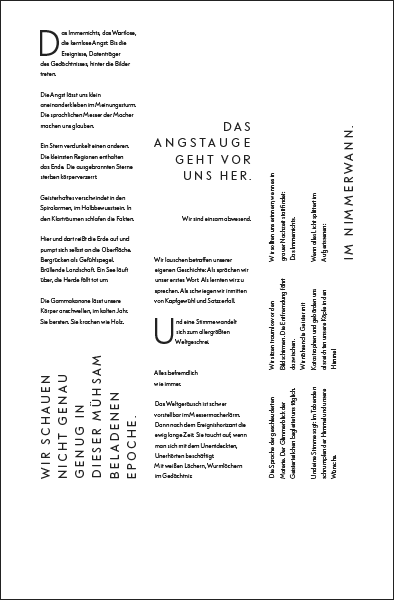
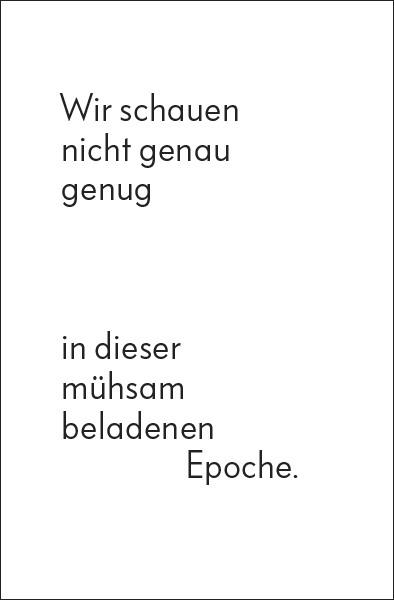
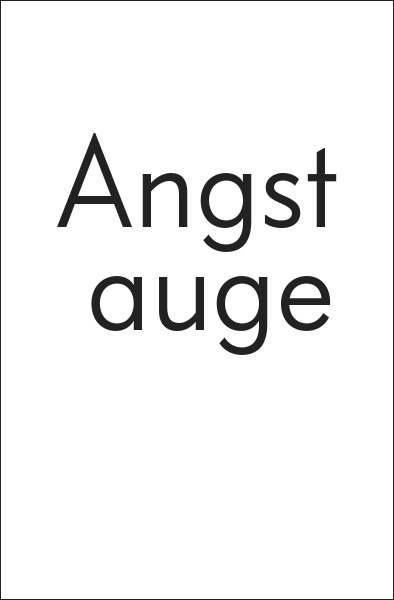
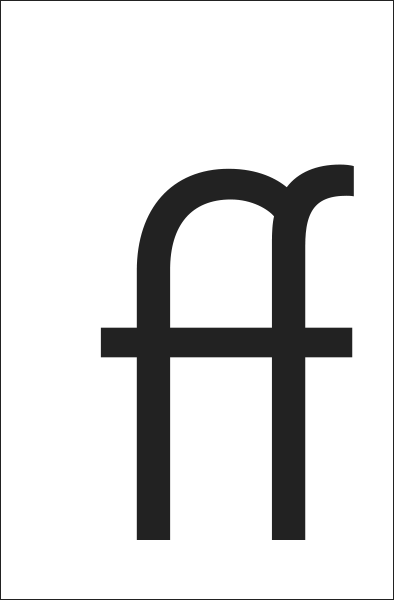
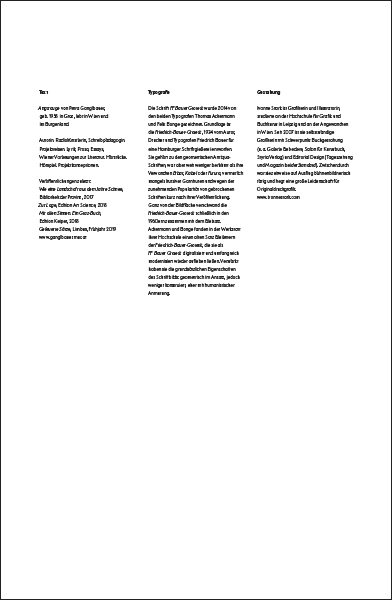
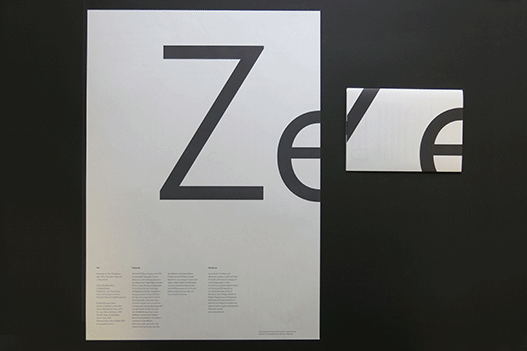
Typografie
Die Schrift FF Bauer Grotesk wurde 2014 von den beiden Typografen Thomas Ackermann und Felix Bonge gezeichnet. Grundlage ist die Friedrich-Bauer-Grotesk, 1934 vom Autor, Drucker und Typografen Friedrich Bauer für eine Hamburger Schriftgießerei entworfen. Sie gehört zu den geometrischen Antiqua-Schriften, war aber weit weniger berühmt als ihre Verwandten Erbar, Kabel oder Futura, vermutlich mangels kursiver Garnituren und wegen der zunehmenden Popularität von gebrochenen Schriften kurz nach ihrer Veröffentlichung. Ganz von der Bildfläche verschwand die Friedrich-Bauer-Grotesk schließlich in den 1960ern zusammen mit dem Bleisatz. Ackermann und Bonge fanden in der Werkstatt ihrer Hochschule einen alten Satz Bleilettern der Friedrich-Bauer-Grotesk, die sie als FF Bauer Grotesk digitalisiert und umfangreich modernisiert wieder aufleben ließen. Verstärkt haben sie die grundsätzlichen Eigenschaften des Schriftbilds: geometrisch im Ansatz, jedoch weniger konstruiert, eher mit humanistischer Anmutung.